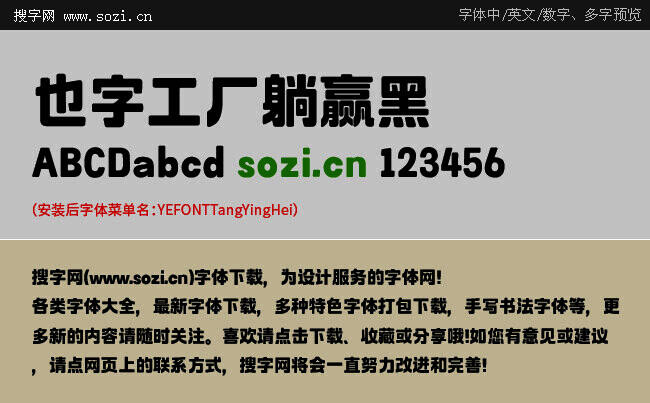
也字工厂躺赢黑
搜字网给大家提供一款也字工厂躺赢黑(非商业使用)中文字体下载,也字工厂躺赢黑字形端庄大方,整体呈现方正,圆润的转折和连接,让字形流畅自然,使字体既有稳重感又不失活泼。 适合应用于海报设计、包装设计等应用(此字体为个人非商用版,商用可以联系:官方网址:https://yefont.com/home,联系方式:13798980448)。